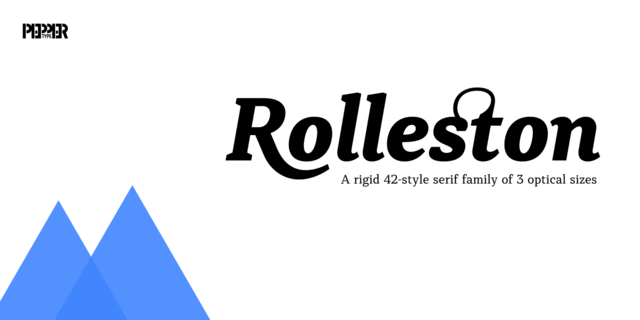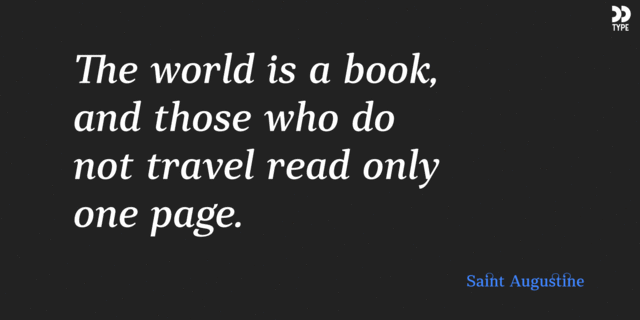
Rolleston Title – часть шрифтового семейства Rolleston. Его 14 начертаний подходят для заголовков в книгах, журналах и на сайтах.
Rolleston – строгое шрифтовое семейство с клиновидными засечками. Гарнитура содержит 42 начертания, по 14 для трех оптических размеров: Text, Title, и Display.
Гарнитура поддерживает десятки языков на латинице и кириллице, содержит различные опентайп-фичи, можество лигатур и большой набор альтернативных глифов. Это позволяет создавать уникальные заголовки и красивые сбалансированные тексты.
Шрифт разработал Олег Лищук в 2018 году.
тонкий, легкий, деликатный, спокойный, ровный, гармоничный, уравновешенный, космополитичный, техничный, современный, точный, логичный, статичный, культурный, образованный, устойчивый, серьезный, умный, твердый, четкий, резкий, худой, вежливый, динамичный, изящный, элегантный, светлый, универсальный, понятный, деловой, умеренный, практичный, оптимальный, доступный, строгий, эффектный, модный, качественный, элитный, дорогой, богатый, городской, отборный, благородный, красивый, мастерский, эстетичный, выразительный, пластичный, приятный, аккуратный, гибкий, Строгий, стабильный, солидный, убедительный, мотивирующий, ответственный, авторитетный, внушительный, суровый, крепкий, тяжелый, плотный, заметный, яркий, активный, броский